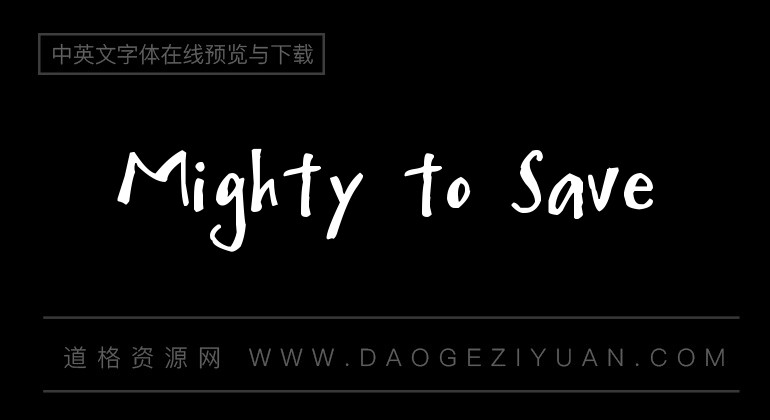
"Mighty to Save" 是一种常用于宗教和基督教相关设计中的字体,它的风格非常简洁、现代、直观。这种字体通常用于海报、教会标志、宣传册和其他类似的宗教设计作品中。 "Mighty to Save" 字体的设计灵感源自于现代书法和手写字体,其字体的线条略带圆润,具有一定的流动性和优美感。它的字母间距适中,易于阅读和辨认,而且字母的形状也非常清晰,不会造成阅读困难。 "Mighty to Save" 字体的颜色通常是黑色或白色,与背景颜色形成对比,使得文字信息更加醒目。这种字体也可以配合其他的装饰元素使用,例如光芒、羽毛、十字架等,以突出主题和宗教元素。 总的来说,"Mighty to Save" 字体非常适合用于宗教和基督教相关设计中,其清晰、简洁的风格与现代感非常吻合,可以让设计作品更具视觉冲击力和吸引力。内容介绍
Mighty to Save是一款非常不错的手写艺术字体,具有很好的视觉感,适合于文化类的宣传设计、商业类品牌的广告和产品包装设计以及个性化文字排版等较多场景。